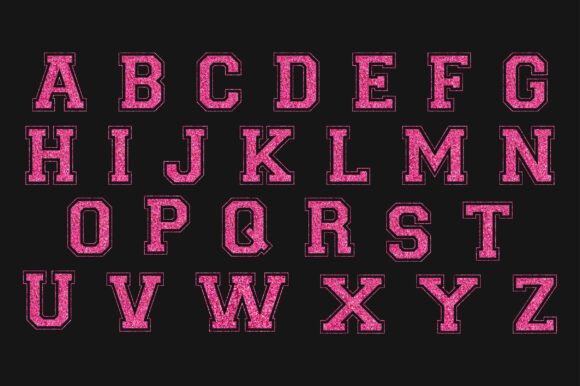
Valentine Pink Glitter Fonts PNG
Encontrar los elementos de diseño adecuados puede ser un desafío, pero Valentine Pink Glitter Fonts PNG ofrece una colección excepcional que eleva tu trabajo al instante.
Elaborado con precisión, Valentine Pink Glitter Fonts PNG proporciona vectores limpios, tipografía suave y una licencia comercial para tu tranquilidad.